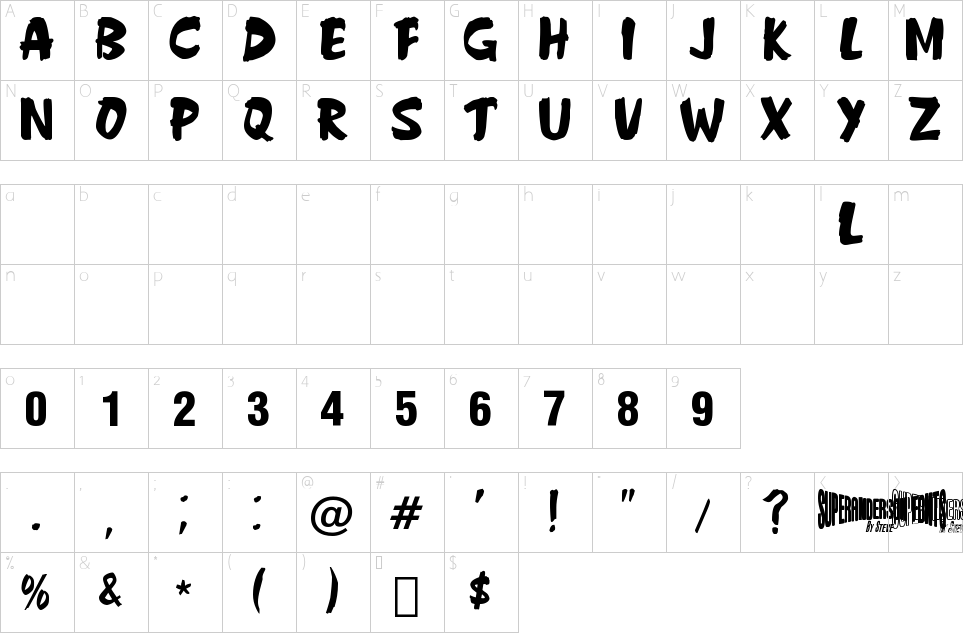
A fonte Anderson Fireball XL5 é uma opção grata para designers e criativos que buscam um efeito visual brilhante e vibrante. Desenvolvida pelo designer Steve Ferrera, esta fonte consegue transmitir emoção e impacto visual em qualquer projeto de design. Com seu design robusto e personalizado, Anderson Fireball XL5 é perfeito para elementos de destaque em layouts de websites, capas de livros, efeitos de texto chamativos em apresentações e muito mais. Recente, a fonte foi baixada 32,145 vezes, demonstrando seu grande valor e popularidade. Para os desenhadores digitais, Anderson Fireball XL5 oferece a combinação perfeita de beleza e personalização, tornando-a uma escolha ótima para a sua próxima projeto visual.